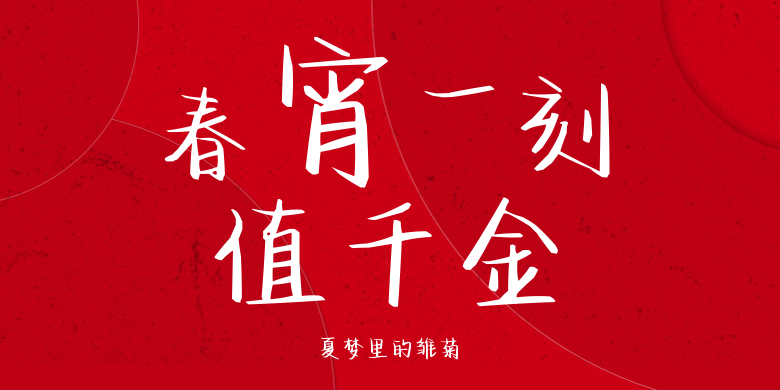
夏梦里的雏菊
夏梦里的雏菊,这款字体结构工整、笔画清晰,兼顾美观与易读性,适用于标题、正文、海报、包装、LOGO 等多种场景。字形优雅稳定,风格百搭耐看,适配日常排版与创意设计,让文字呈现更舒适、更具质感。夏梦里的雏菊一笔一画,皆是细节,以均衡的比例、流畅的线条打造舒适视觉体验,字形端正大气,风格简约现代。无论是商业设计、品牌宣传还是日常排版,都能轻松驾驭,让文字更有格调与力量。夏梦里的雏菊字体下载。